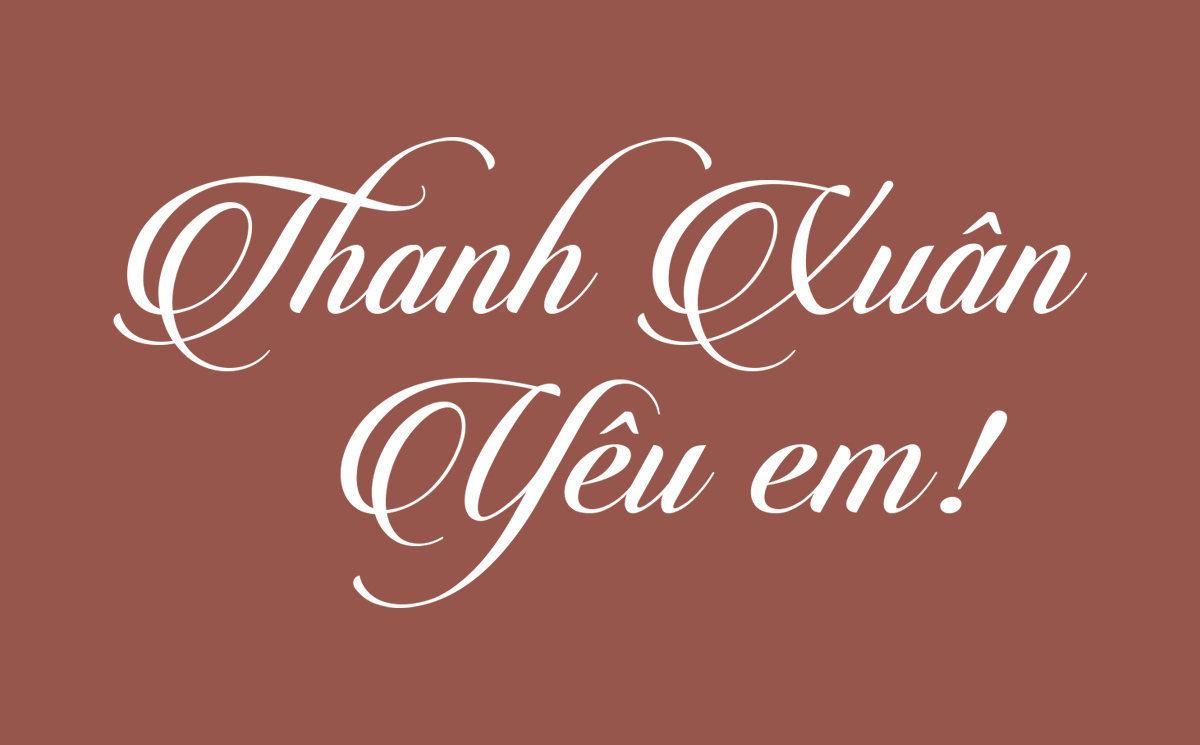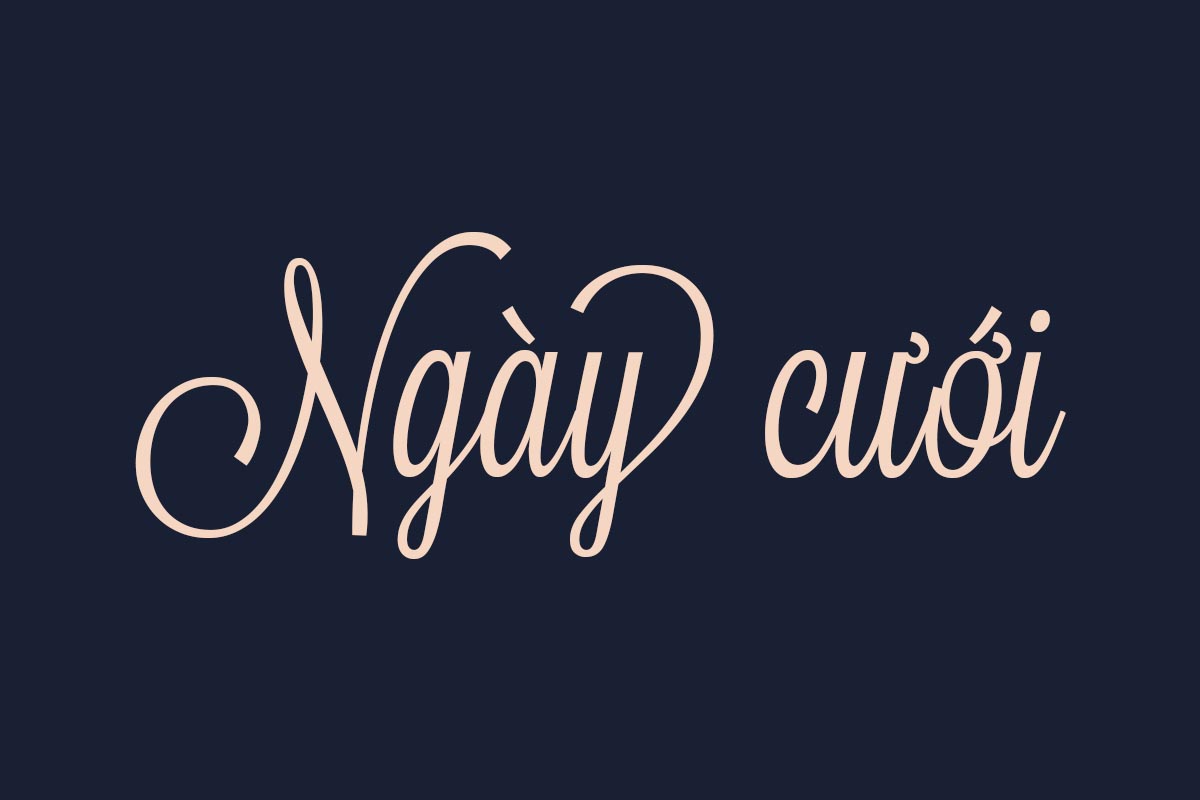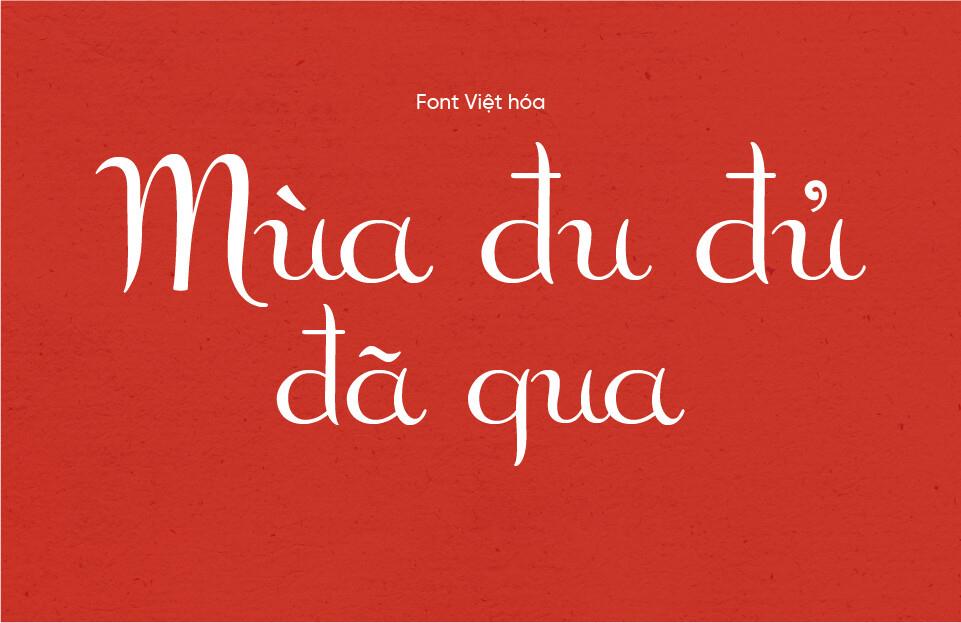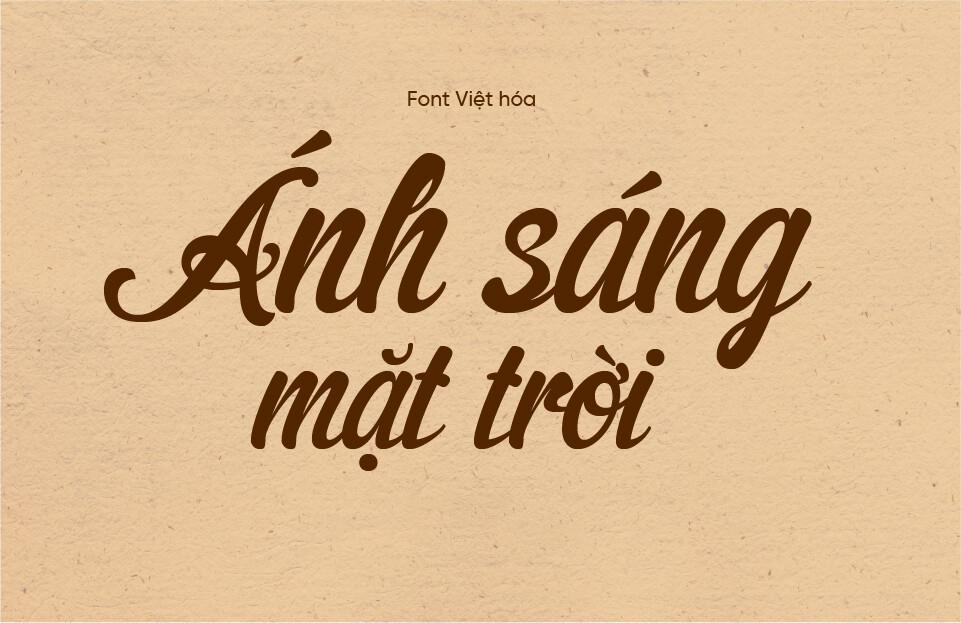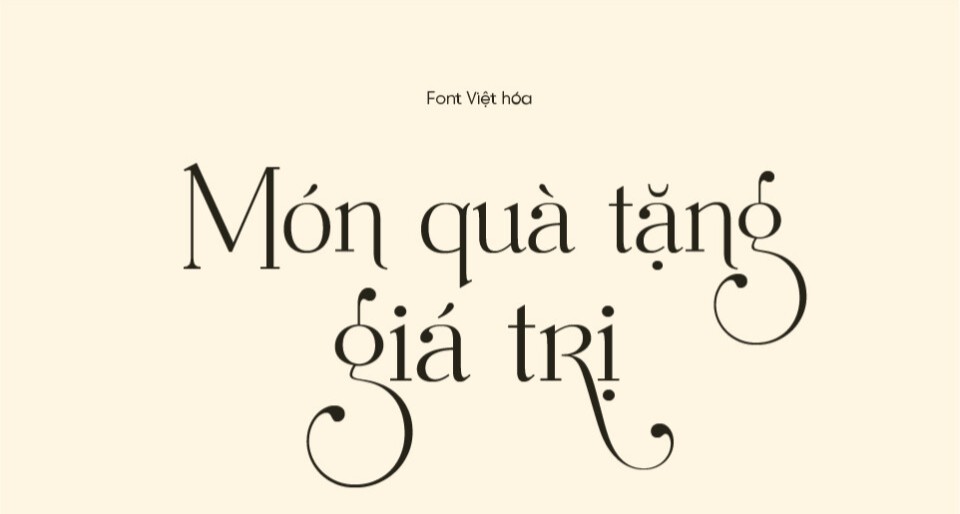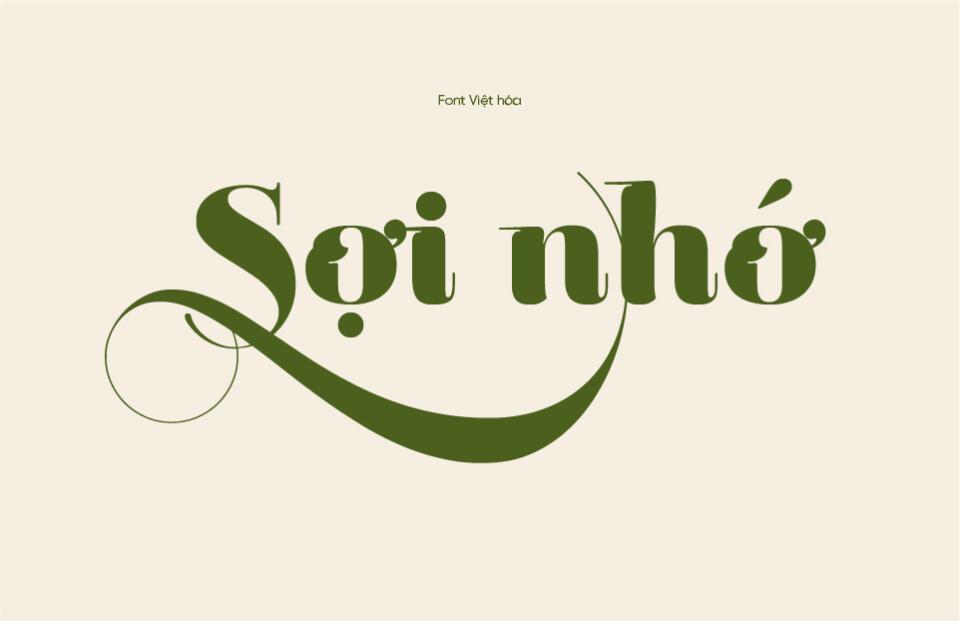
Font UVF
Designer thường gặp khó khăn vì dùng phông chữ chưa Việt hóa khiến các ký tự có dấu bị lỗi sẽ làm giảm giá trị thẩm mỹ của sản phẩm. Xưởng In Viva chia sẻ link download font UVF Việt hóa sắc nét, hỗ trợ tối đa cho việc sản xuất và thiết kế ấn phẩm nhé.
Font UVF là gì?
UVF (Unitech Viet Font) là dự án phông chữ Việt hóa đồ sộ và uy tín. Đặc trưng của UVF là sự đa dạng phong cách, từ Sans-serif hiện đại đến Script mềm mại, đáp ứng mọi nhu cầu thiết kế từ ngành công nghệ đến mỹ phẩm. Điểm mạnh của font chữ UVF là sự căn chỉnh Kerning và dấu tiếng Việt cực kỳ cân đối, giúp thiết kế chuyên nghiệp.
Bộ font UVF luôn đảm bảo độ ổn định cấu trúc vector. In Viva ưu tiên sử dụng dòng phông này cho các dự án ép kim, dập nổi vì các nét chữ của UVF rất sắc sảo, không bị lỗi điểm neo khi gửi file sang máy gia công tự động, đảm bảo thành phẩm luôn hoàn hảo.
Bộ font UVF tiếng việt sang trọng
04 ứng dụng font UVF Việt hóa trong thiết kế và sản xuất
Sự linh hoạt của bộ phông UVF giúp nâng tầm giá trị cho nhiều dòng sản phẩm gồm có:
• Thiết kế logo và nắp hộp quà Tết: Sử dụng các bộ Script UVF cho lời chúc “Vạn sự như ý” tạo vẻ đẹp sang trọng và ấm cúng cho hộp quà.
• Sản xuất bao bì dược phẩm: Các phông Sans-serif của UVF giúp thông tin hướng dẫn trên hộp thuốc rõ ràng và dễ tiếp cận người dùng.
• In logo sản phẩm: Logo dùng font UVF in UV lên sạc dự phòng, bình giữ nhiệt tạo vẻ ngoài hiện đại và đẳng cấp.
• Đồng bộ bộ nhận diện văn phòng: Từ danh thiếp đến túi giấy đựng quà đều được đồng bộ hóa phông chữ một cách tinh tế.
Font UVF Việt hóa
Font UVF Việt hóa nghệ thuật
04 lưu ý khi sử dụng font chữ UVF Việt hóa
Để ấn phẩm in ấn đạt chất lượng cao, designer cần ghi nhớ các điểm sau:
• Tối ưu đường Path cho gia công bế nổi: Kỹ thuật viên cần làm mượt đường path vector của font UVF để khuôn bế dập nổi logo không bị xơ giấy mỹ thuật.
• Tận dụng ký tự thay thế: Nhiều font UVF có các nét nối Ligatures nghệ thuật, hãy dùng chúng để tạo điểm nhấn cho logo.
Bộ font UVF tiếng việt
Font UVF Việt hóa sang trọng